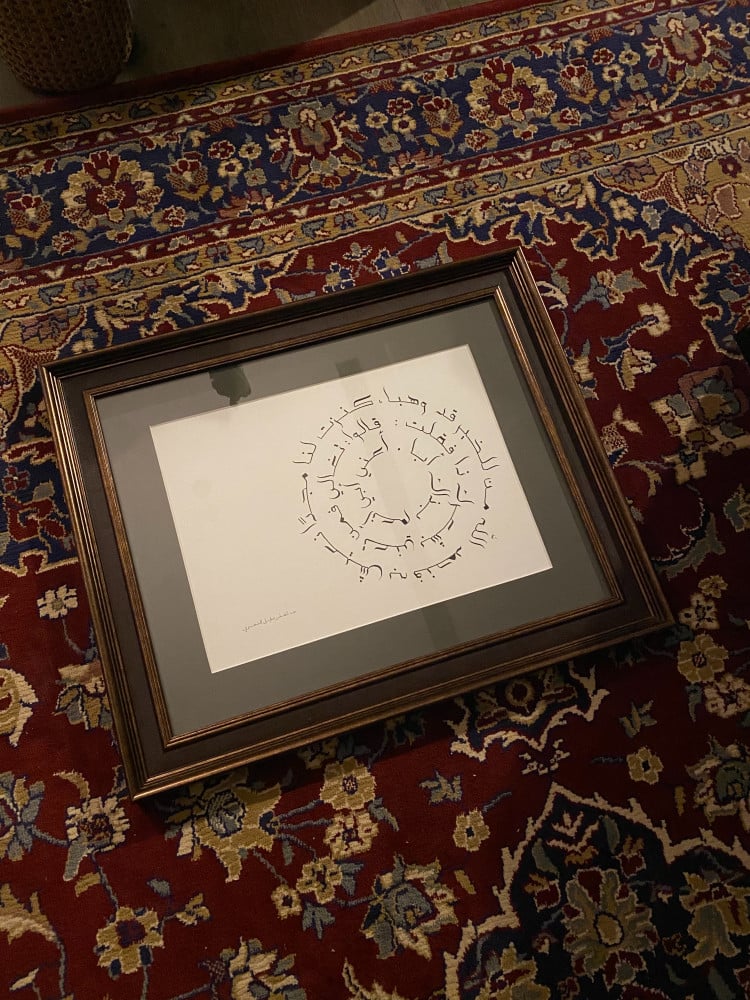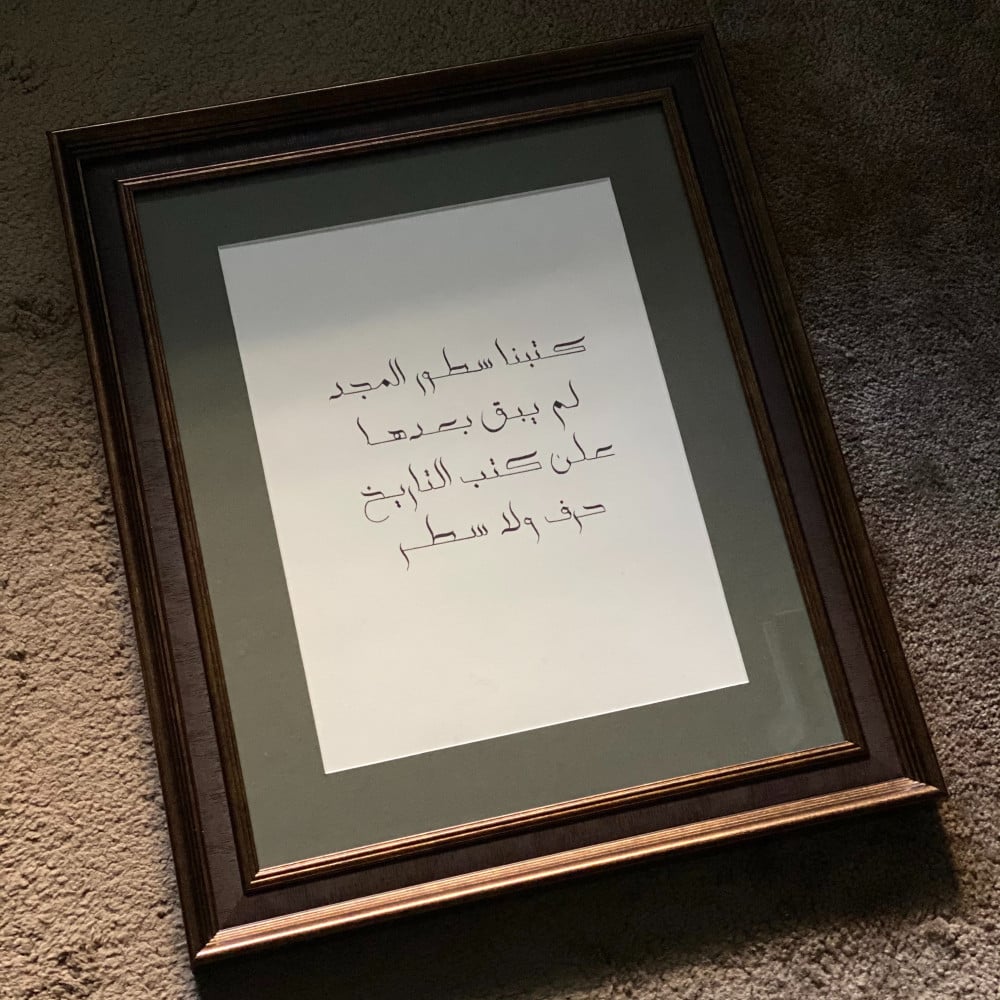
إطار خشب/جوانب خضراء بجملة من اختيارك
اكتب عبارة أو اختر بيت من قصيدة تعجبك وحولها إلى كتابة بالخط العربي بإبداع الخطاط ✨
تحاط المخطوطة بحواف عنابية وإطار خشب من الطراز العالي ✨